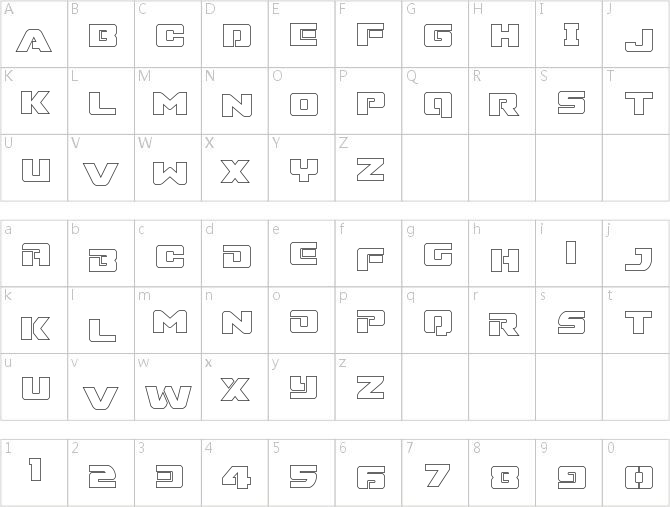
Super Commando Outline
Super Commando Outline介紹
Super Commando Outline字體字庫是一款讓人賞心悅目、百看不厭的英文字體,適合各類廣告和產品包裝設計應用,字體大小0.04MB,格式為ttf字體,上傳用戶是sunlight,作者/版權方為未知